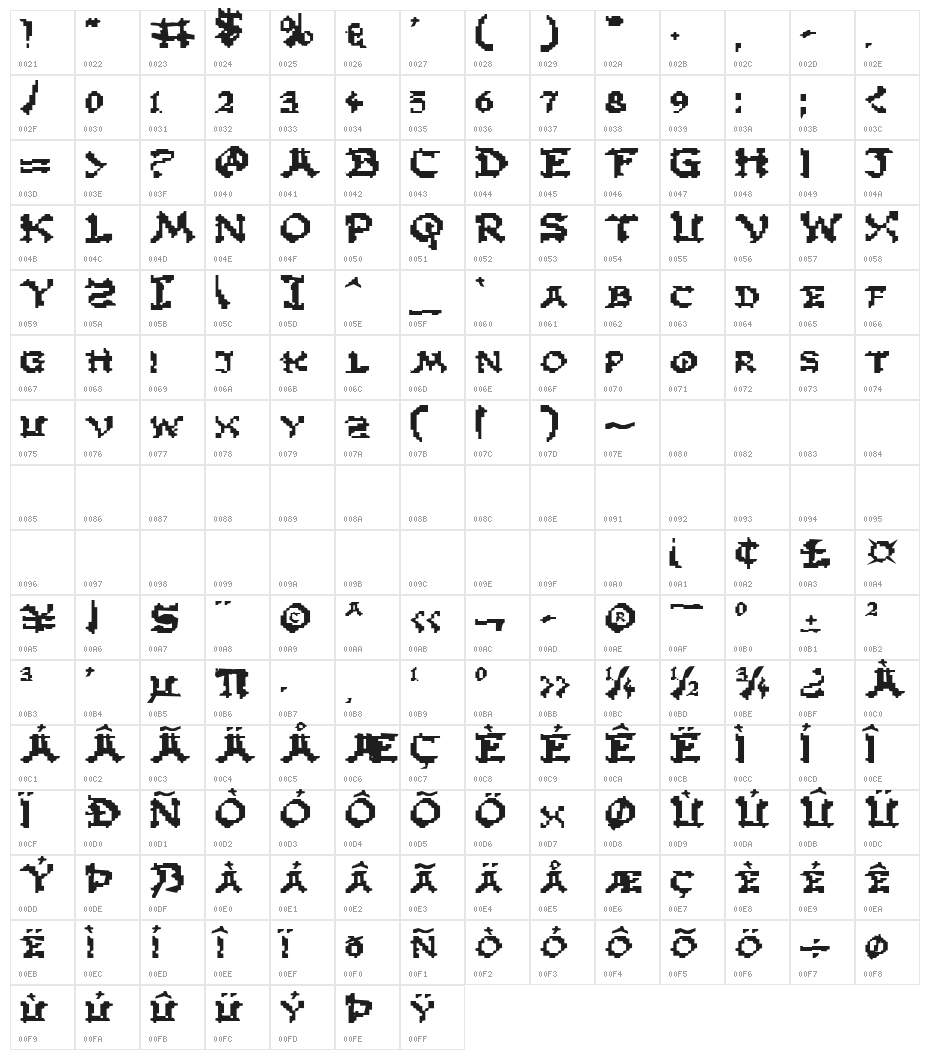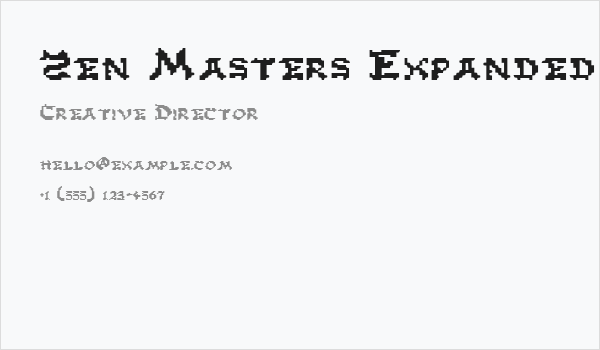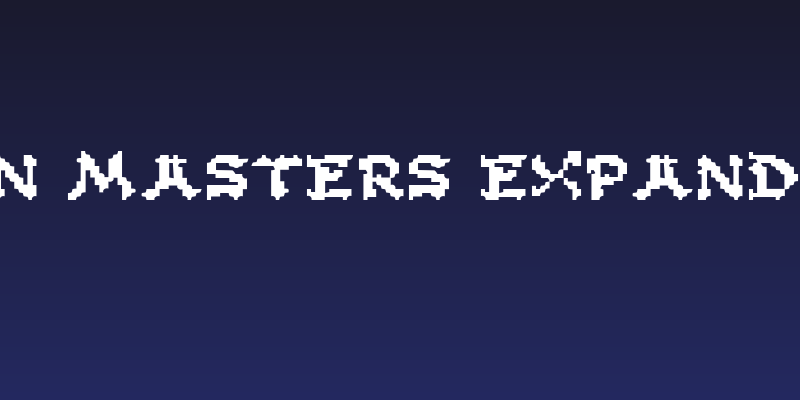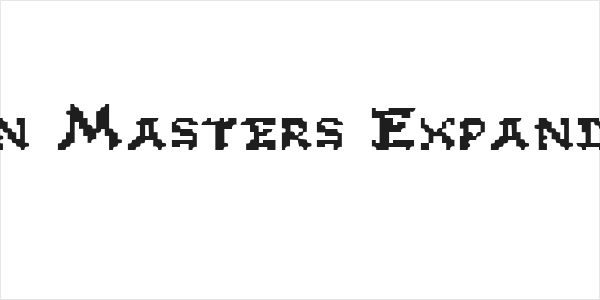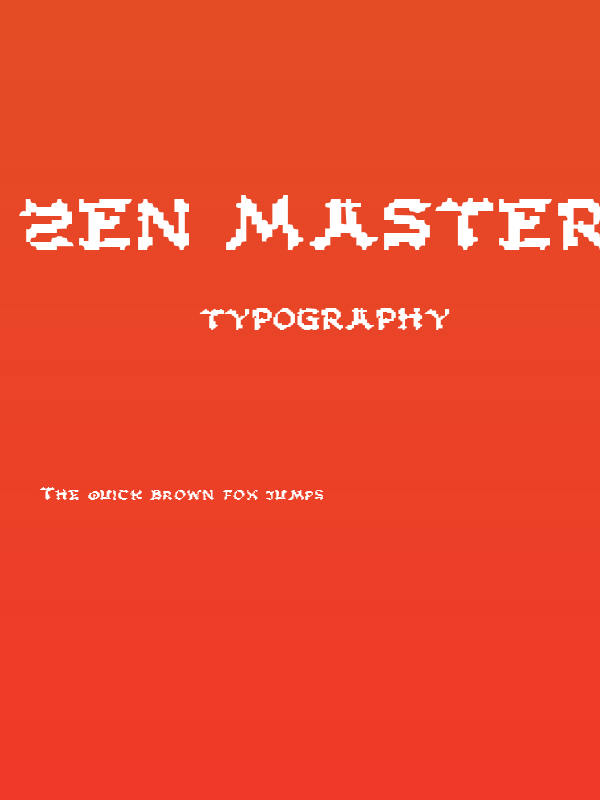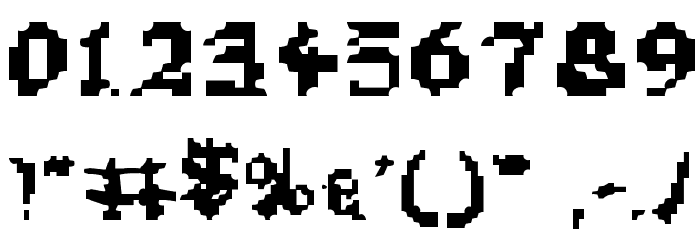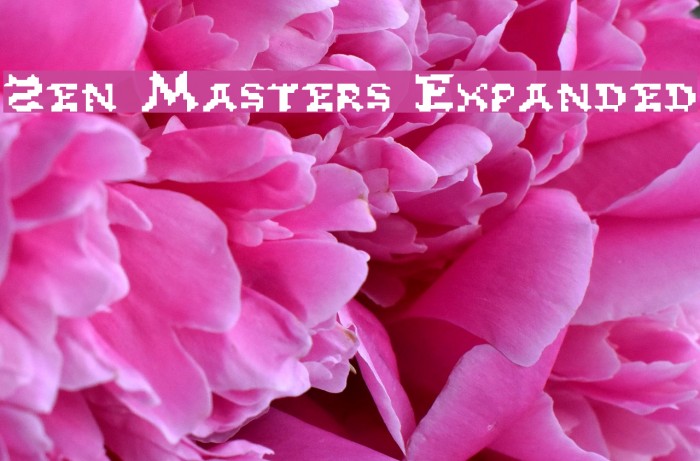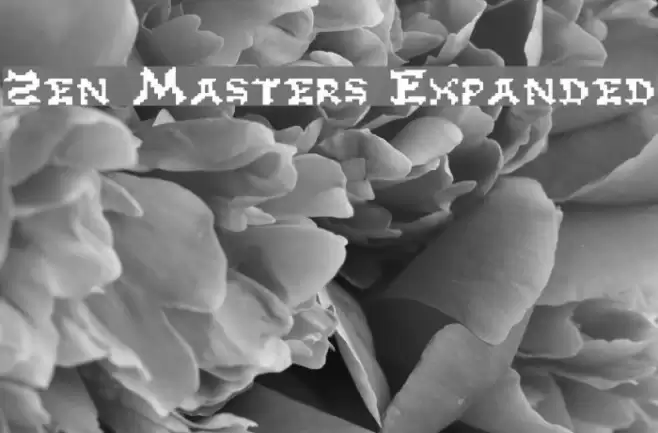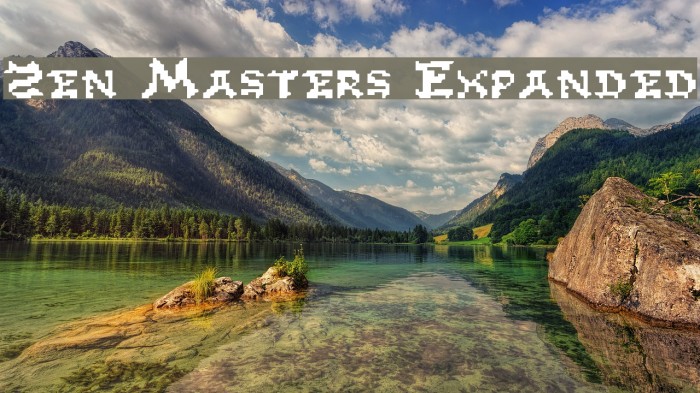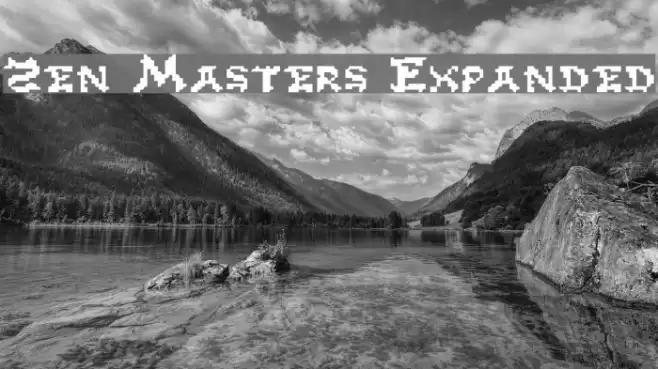
Zen Masters Expanded Font
| Projets proposés | Ideal for video game graphics, tech-themed posters, digital art projects, and branding for technology companies. |